16 Font Luar Angkasa untuk Proyek Desain Luar Dunia ini untuk tahun 2023
Diterbitkan: 2023-02-28Seringkali merupakan tantangan untuk memposisikan bisnis sebagai berpikiran maju dan inovatif. Ini terutama berlaku untuk bisnis teknologi dan industri lain yang berada di ujung tombak. 'Fon luar angkasa' sangat ideal, karena langsung membangkitkan perasaan semacam itu. Namun, Anda juga bisa menerapkannya pada acara seperti club night, jenis musisi tertentu seperti pertunjukan Electronic Dance Music (EDM), dan lainnya.
Untuk posting ini, kami akan mengumpulkan beberapa font ruang terbaik yang dapat kami temukan, dan memberi Anda beberapa tip tentang cara menggunakannya. Pertama, mari kita bicara tentang bagaimana memilih font yang tepat untuk kebutuhan Anda.
Cara Memilih Font Ruang yang Tepat untuk Proyek Anda
Kami akui, istilah "font spasi" adalah istilah yang luas yang dapat mencakup banyak basis berbeda. Daftar yang akan kami sajikan mencerminkan cakupan yang luas ini. Beberapa font akan terlihat seperti berasal dari planet lain, sedangkan yang lain 'kitsch' dan nostalgia.
Terlepas dari itu, ada tiga aspek yang ingin Anda ingat saat memilih font spasi yang tepat:
- Pastikan itu dapat dibaca. Anda akan melihat bahwa beberapa font pada daftar ini memiliki huruf khusus yang tidak sesuai dengan konvensi tipikal. Karena itu, pastikan Anda tetap menjaga keterbacaan tetap tinggi, terlepas dari bagaimana Anda menggunakan font spasi.
- Pastikan itu sesuai dengan proyek Anda. Tentu saja, Anda ingin memastikan bahwa font atau jenis huruf yang Anda pilih sesuai untuk proyek Anda. Tidak akan cukup untuk menampar font ruang lama mana pun. Dengan ini, Anda ingin membangkitkan perasaan pembaca Anda.
- Pilih font pasangan yang bagus. Sebagian besar font dalam daftar ini adalah untuk tampilan. Dengan demikian, Anda akan menginginkan pasangan yang dapat dibaca yang dapat Anda gunakan untuk body copy juga. Desain klasik seperti Arial dan Helvetica sangat ideal (lebih banyak dalam satu menit.)
Dari sini, Anda dapat mulai menelusuri beberapa font ruang yang tersedia untuk melihat apakah cocok dengan proyek Anda.
Cara Meniru Font NASA dan SpaceX
Jika proyek Anda membutuhkannya, Anda dapat menyajikan perkiraan kasar dari tipografi NASA dan SpaceX. Meskipun Anda tidak ingin menganggap proyek Anda resmi, parodi dapat berhasil dalam beberapa kasus.
Selama bertahun-tahun, NASA telah menggunakan dua logo berbeda – lambang 'bakso' dan 'cacing'. Meskipun keduanya bukan tipografi lengkap, Anda dapat menggunakan font gratis untuk mendekat. Pertama, Nasalisasi adalah perkiraan yang mendekati cacing:
Untuk mereplikasi lambang, Anda dapat menggunakan Nasa Serif:
Sama seperti institusi lain dengan branding, NASA memiliki pedoman tipografi dan penggunaan yang mungkin relevan tergantung pada proyek Anda. Namun, Helvetica Bold digunakan di sisi pesawat ruang angkasa. Ini biasanya font sistem yang tidak hanya dapat mengeluarkan getaran 'eksplorasi luar angkasa', tetapi juga font yang dapat dibaca dan diakses.
Sedangkan untuk SpaceX, logonya menggunakan desain khusus yang sekali lagi bukan jenis huruf lengkap. Cara terdekat yang akan Anda dapatkan adalah menggunakan sesuatu seperti Bank Gothic. Namun, ini bukan pencocokan yang tepat, jadi Anda mungkin harus mencari font ruang lain untuk kebutuhan Anda.
16 Font Luar Angkasa untuk Proyek Desain Luar Dunia Ini
Selama sisa pembahasan ini, kita akan melihat beberapa font luar angkasa fantastis yang sesuai dengan berbagai jenis proyek.
1. MBF Space – Pilihan Teratas Kami
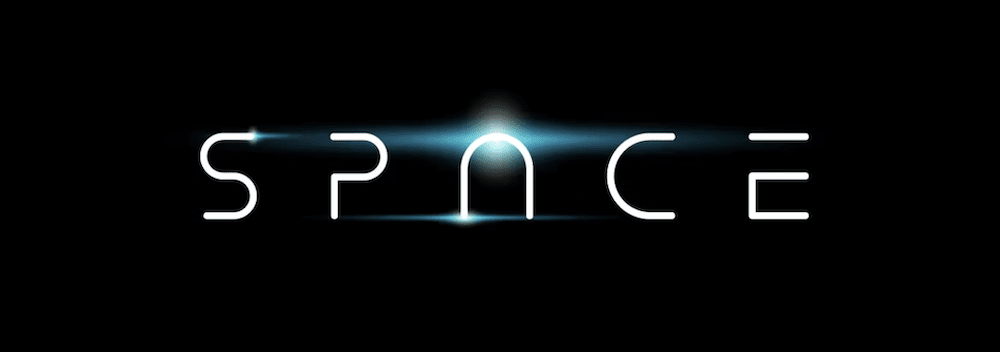
Font MBF Space adalah salah satu yang terbaik yang tersedia, dan merupakan pilihan utama kami. Meskipun font ini tidak akan pernah menjadi body copy, Anda akan menggunakannya untuk heading, display, poster, workmark, dan banyak lagi.
Ini adalah font ruang yang tipis dan minimalis dengan huruf khusus. Namun, masih terbaca pada ukuran yang lebih kecil. Tepinya yang membulat membantu dalam hal ini, dan dengan demikian, Anda dapat menerapkan semua jenis spasi agar sesuai dengan dimensi Anda.
Mengapa Ini Pilihan Teratas Kami
MBF Space sangat serbaguna. Anda dapat menggunakannya untuk mengingat kembali film sci-fi tahun 70-an seperti Alien di samping font seperti Alien League dan Future Condensed Extra Bold. Sebaliknya, Anda juga dapat menggunakan ini untuk aplikasi modern yang harus terlihat inovatif. Secara keseluruhan, MBF Space minimalis, namun khas dan fleksibel.
2. Meteorit
Kami berani bertaruh bahwa Meteorit hanya akan memiliki sedikit kegunaan yang layak. Namun, sebagai font luar angkasa, ini adalah pemenang yang tak terbantahkan untuk tampilan dekoratif.
Anda akan mendapatkan huruf besar dan kecil, lengkap dengan angka. Setiap desain huruf hadir dengan 'meteor damage', dan meskipun penyajiannya unik, juga menawarkan keterbacaan dalam ukuran yang lebih kecil.
3. Ruang Kota
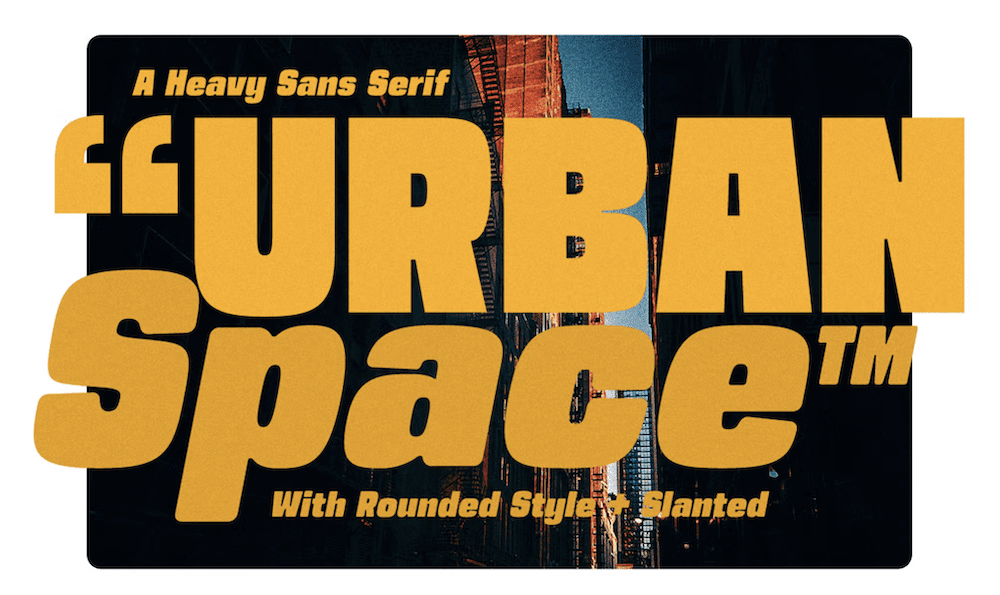
Urban Space adalah contoh pertama dalam daftar font ruang nostalgia ini. Banyak desainer akan memilih font minimalis hiper-modern, atau sesuatu yang berasal dari ide perjalanan ruang angkasa tahun 50-an.
Font spasi ini adalah jenis huruf sans-serif berat yang menyediakan huruf besar dan kecil, angka, dan ligatur lainnya. Ini berarti Anda akan dapat mencampur dan mencocokkan font untuk mencapai desain akhir Anda.
4. Aurora
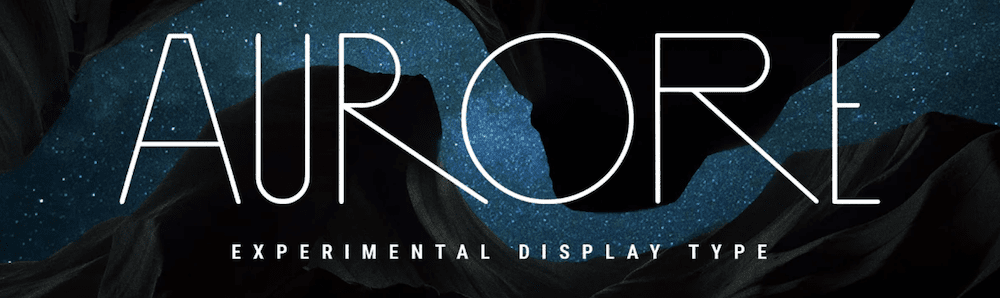
Aurore adalah font luar angkasa premium yang memiliki getaran intergalaksi tahun 60-an. Faktanya, kami juga akan menggunakan yang ini untuk proyek lain, seperti fashion atau branding mewah.
Kami menyukai betapa serbagunanya Aurore. Anda mendapatkan hampir 80 varian huruf berbeda, dan dua font untuk tipografi – reguler dan tebal. Harga desktop dan font web mulai dari $14, tetapi naik menjadi $140 untuk penggunaan dalam aplikasi.
5. Huruf Spasi
Space Font adalah contoh paling menyenangkan di daftar kami. Ini bukan desain formal, jadi kami akan menggunakan ini untuk aplikasi literal yang ditujukan untuk anak-anak. Font siluet ini menggunakan planet, roket, bintang, dan lainnya untuk memberi tanda baca pada setiap huruf, dan dalam beberapa kasus menentukan bentuk huruf.
Anda juga dapat memilih untuk menggunakan huruf tanpa stempel dan siluet, yang memberikan fleksibilitas. Kami sangat menyukai versi 'non-stempel', tetapi mereka tidak cukup memotongnya sebagai font ruang 'bonafide'.
6. Gelombang masa depan
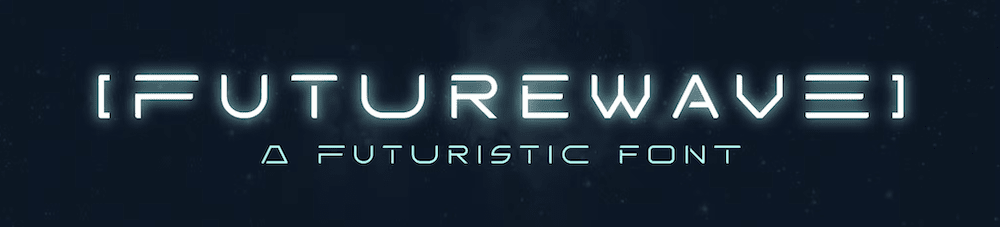
Super-futuristik dan bergaya, Futurewave adalah salah satu font yang kami ingin lihat digunakan dalam video game. Beberapa huruf dengan desain khusus (seperti 'A') memiliki banyak varian. Dengan pilihan desain yang tepat, kami dapat melihat Futurewave juga digunakan untuk musik.
Meskipun Anda tidak mendapatkan huruf kecil di sini, Anda mendapatkan angka dan simbol lainnya. Padahal, Anda mungkin ingin menggunakan font spasi ini pada ukuran besar, karena menawarkan keterbacaan yang lebih sedikit pada ukuran yang lebih kecil.
7. Batas Luar
Outer Frontier adalah font ruang fleksibel yang mungkin melihat penggunaan di luar yang dimaksudkan. Desainnya mirip dengan layar LCD digital, yang berarti Anda dapat menekan nomornya untuk melayani elemen seperti penghitung waktu mundur dan waktu acara sebagai efek yang menonjol.
Untuk tampilan font yang kreatif, Outer Frontier juga memberikan tingkat variasi yang baik. Anda mendapatkan akses ke huruf besar dan kecil, angka, tanda baca, dan berbagai jenis file.
8. Ruang Armada
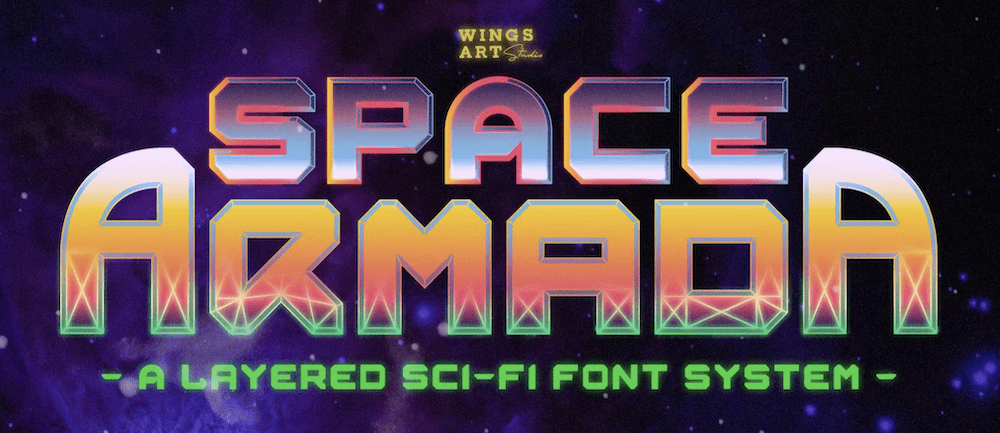
Seperti halnya Meteorite, Space Armada hanya cocok untuk beberapa aplikasi, tetapi menawarkan kesesuaian yang baik saat Anda menggunakannya. Ini cocok dengan kotak yang sama dengan Aurore dan Urban Space karena mengingatkan kembali ke masa lalu – kali ini tahun 80-an.
Dengan demikian, Space Armada akan melihat banyak kegunaan pada poster untuk malam retro, dan di mana pun Anda perlu merujuk getaran sci-fi 'jadul'. Anda juga dapat membuat beberapa desain unik menggunakan berbagai garis luar, gambar rangka, dan isian. Space Armada akan menjadi pilihan utama kami jika tidak terlihat begitu unik!
9. Keliaran Roket
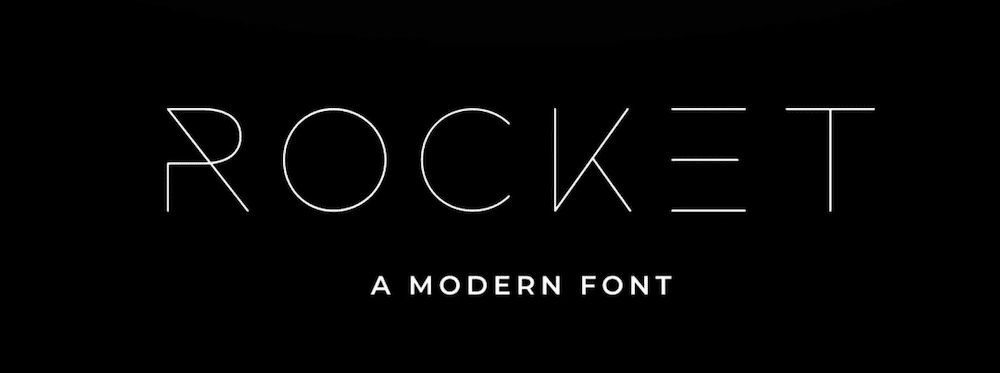
Inilah font minimalis dan sederhana lainnya yang bekerja dengan baik di berbagai ceruk. Anda dapat menggunakan Rocket Wildness untuk merek mewah, proyek modern, dan situs feminin. Namun, ini juga salah satu font ruang yang paling mudah beradaptasi.
Anda tidak mendapatkan banyak variasi di sini. Ada huruf besar, simbol, dan angka. Namun, sebagai font tampilan, ini memotong mustard dan terlihat mudah dibaca meskipun ada huruf khusus. keliaran roket adalah $17 untuk versi desktop, tetapi lisensi webfont hampir dua kali lipat, pada $30.
10. ledakan bintang
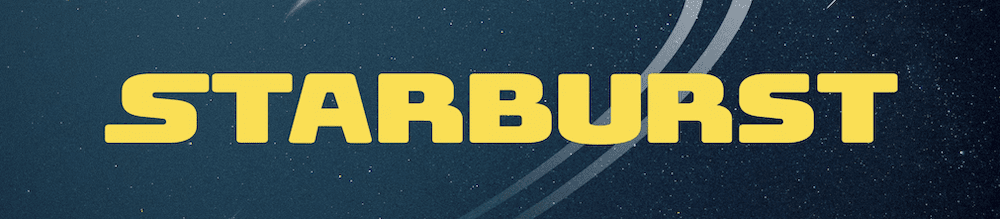
Kami menyebutkan font film sebelumnya dengan MBF Space, dan Starburst meniru franchise film terkenal lainnya. Ini bukan salinan satu per satu, tetapi beberapa huruf memanjang mengingatkan pada Start Wars. Namun, itu cukup untuk membedakannya sebagai font ruangnya sendiri.
Startburst juga merupakan font yang fleksibel. Ini termasuk huruf besar dan kecil, pengikat, angka, simbol, dan alternatif.
11. Ruang Kosong
Kita bisa menempatkan Blank Space dengan mantap dalam kategori font space yang retro namun modern. Ini adalah sans-serif besar yang hadir dengan banyak opsi huruf alternatif.
Kami menyukai tampilan alternatif tersebut, dan ini memberikan font desain ramping yang akan lebih cocok daripada ruang atau aplikasi futuristik. Anda ingin menggunakan font ini dalam ukuran besar – jadi tampilan akan ideal.
12. Rakupin
Pengecoran font Nomores menghasilkan banyak tipografi dengan garis yang mirip. Meskipun kami dapat menampilkan Gobrac atau Jcorbs, kami akan menggunakan Raqupine. Ada beberapa alasan untuk ini.
Pertama, kami menyukai tampilan futuristik dan bentuk hurufnya. Kita bisa melihat ini sebagai font judul untuk produk teknologi, atau digunakan dalam video game. Terlebih lagi, ini memberi kita getaran Star Trek, karena mirip dengan penggunaan Microgramma Bold Extended di alam semesta.
13. Habitat Luar Angkasa MBF
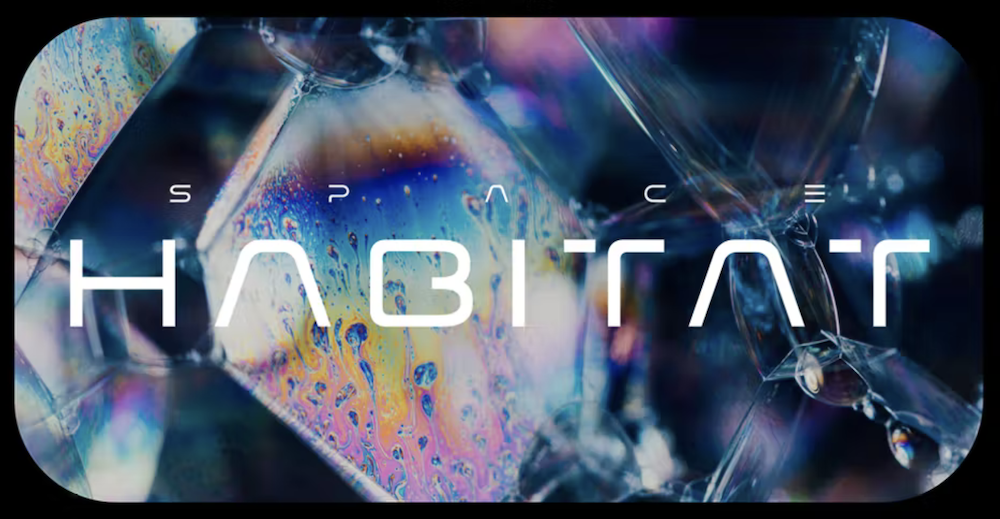
Meskipun Space Bandit berasal dari jenis pengecoran yang berbeda, Anda dapat melihat kesamaan antara ini dan Raqupine. Faktanya, kami menyukai bagaimana ini merupakan jalan tengah antara font terakhir dan MBF Space (yang lain dari pengecoran yang sama.)
Font spasi sepertinya tidak dapat dibaca, tetapi Anda dapat bekerja dengan ini pada ukuran yang lebih kecil daripada yang lain di daftar ini tanpa tekanan. Secara keseluruhan, ini adalah salah satu font luar angkasa favorit kami.
14.Scarlex
Kita bisa mengelompokkan ini dengan font ruang retro lainnya seperti Aurore dan Urban Space. Scarlex adalah desain sci-fi tahun 60-an lainnya yang menawarkan garis luar yang unik.
Font menawarkan kepribadian dalam sekop, meskipun kami tidak tahu apakah Scarlex memiliki banyak aplikasi di luar sci-fi. Namun, untuk desain tersebut, Scarlex adalah jenis huruf sans serif yang bekerja dengan baik terlepas dari apakah Anda menggunakan huruf besar atau huruf kecil.
15. Ruang Berongga
Tetap bersama kami saat kami menyajikan font spasi paling kiri di daftar ini. Ya, Hollow Space adalah font retro lain yang tidak memiliki hubungan langsung dengan relung ruang dan futuristik. Namun, kami pikir itu akan sempurna untuk jenis proyek yang tepat.
Bayangkan jika Anda perlu menampilkan poster parodi unik tahun 60-an, katakanlah, Lost in Space. Ini akan menjadi sempurna. Itu bisa membuat sampul buku juga, dan merupakan contoh bagus dari font spasi yang memperkaya desain tanpa berlebihan. Lebih baik lagi, ia menawarkan set tipe paling multibahasa dalam daftar ini, lengkap dengan aksen jika Anda membutuhkannya.
16. Tangan Hamburg
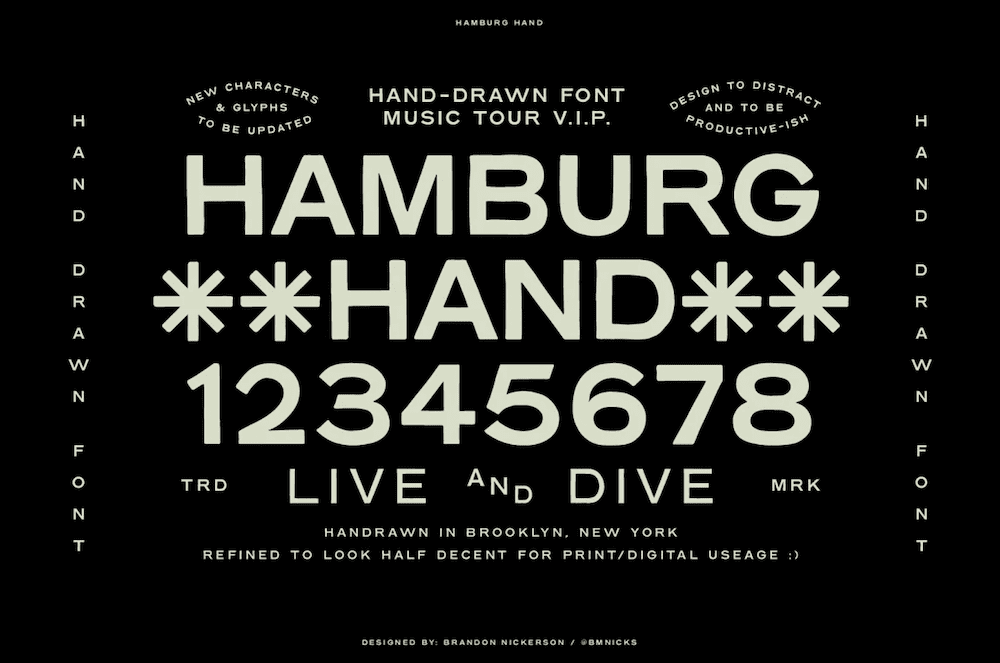
Font ruang terakhir kami dalam daftar ini sekali lagi bukan font yang akan Anda kaitkan dengan ceruk. Hamburg Hand adalah jenis huruf yang menawarkan variasi tebal, reguler, dan ringan. Anda juga akan menemukan huruf besar dan huruf kecil.
Sementara font mengambil isyarat dari tipe Jermanik lama (karena itu namanya,) kita dapat melihat ini digunakan sebagai font luar angkasa yang bersahaja untuk membantu mengatur suasana hati agar sesuai dengan tema eksplorasi ruang angkasa awal. Hamburg Hand berharga $12 untuk lisensi webfont dan desktop, yang mencuri tipografi yang begitu menarik.
Kesimpulannya
Untuk membangkitkan perasaan eksplorasi, pemikiran ke depan, dan masa depan, font luar angkasa bisa jadi ideal. Semua font tampilan ini memberikan sesuatu yang berbeda, yang berarti Anda akan memiliki banyak pilihan untuk proyek Anda.
Font seperti Hamburg Hand, Blank Space, dan Urban Space semuanya retro dan nostalgia. Sesuatu seperti Space Armada hanya akan memiliki sedikit kegunaan, tetapi akan unggul jika cocok. Namun, font luar angkasa seperti MBF Space sangat ideal untuk semua jenis poster, pamflet, tajuk, dan lainnya – terlepas dari huruf khusus.